Exempel på nya företagstypsnitt som vi har varit med och tagit fram:
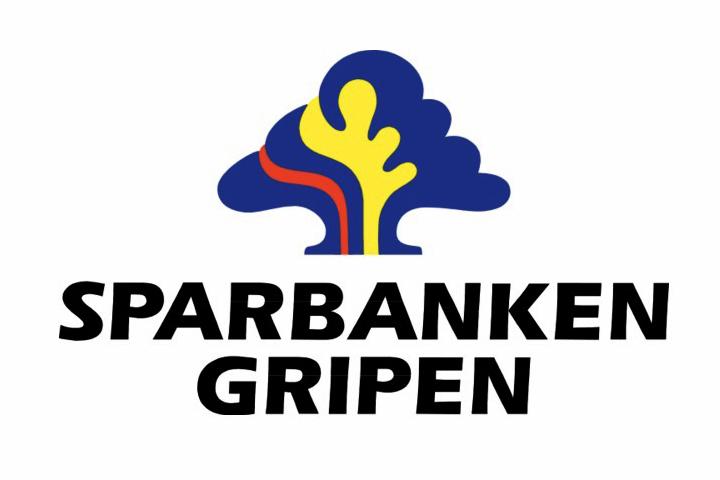
Vårt allra första uppdrag från 1990! Sparbanken hade anlitat en formgivare i New York som hade handritat ett nytt helversalt typsnitt i samband med bankens omarbetade grafiska identitet (med ny stilistisk logotyp och allt). Vi fick detta handritade underlag, scannade in och vektoriserade hela alfabetet och tog fram vårt allra första unika företagstypsnitt.
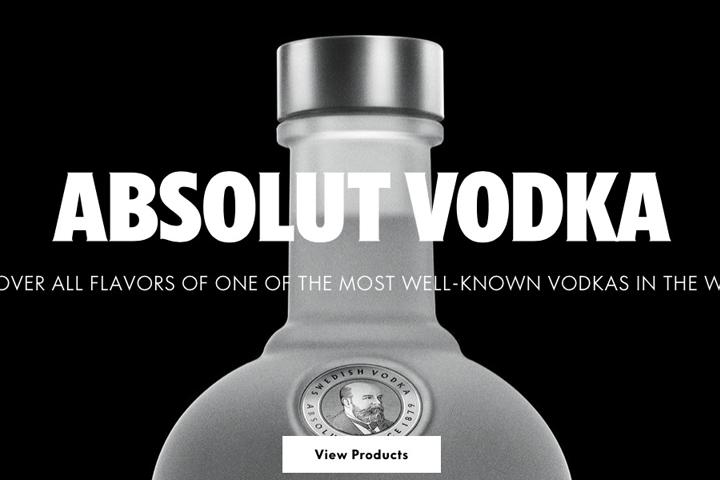
Vi tog fram tre nya vikter med fyra tillhörande kursiver (varav en bakåtlutad), två kondenserade vikter samt en graverad, samtliga för både print och webb (de senare med utökat manuell specialhintning). Förlagan var Absoluts tidigare typsnitt Futura, men med en lite mer samtida touch med influenser från modern humanistisk grotesk.
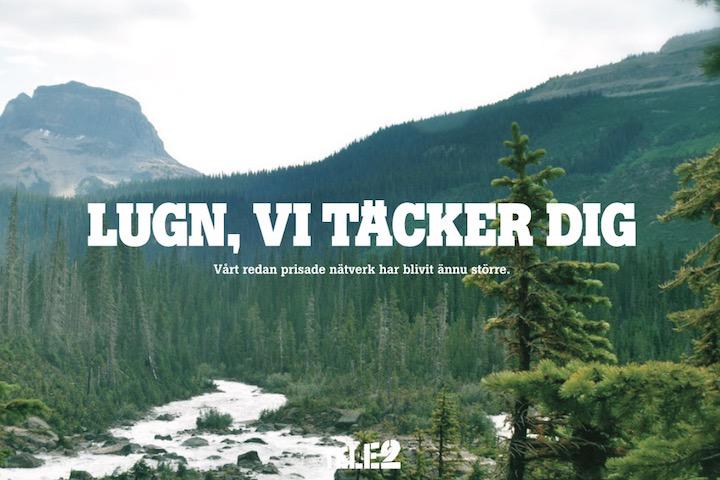
Med Tele2:s befintliga slabseriff-typsnitt som idémässig förlaga fick vi i uppdrag att rita ett helt nytt unikt typsnitt till Tele2, vilket resulterade i de två vikterna Regular och Bold jämte kursiver i såväl rubrik- som löptextanpassat tillriktningsutförande. Vi kompletterade senare samtliga fonter med kyrilliska (ryska) versioner, och ritade även en extrafet helversal Heavy-vikt (enbart avsedd för rubriksättning).
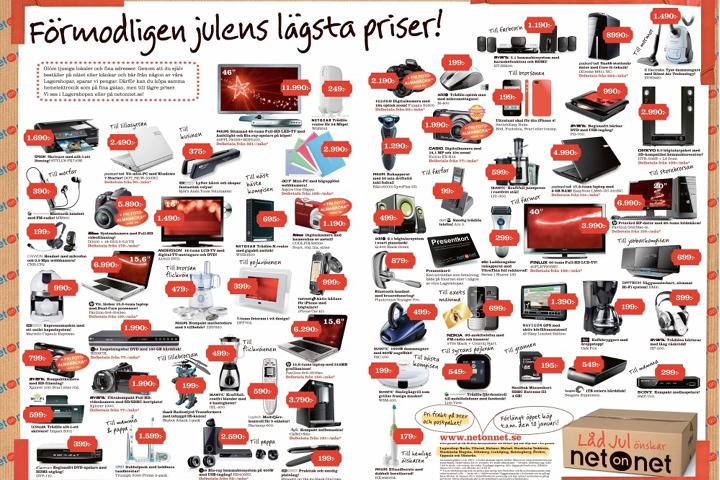
Designbyrån Garbergs behövde ett nytt kampanjtypsnitt till NetOnNet och kom till oss med ett handritat underlag. Vi skannade in, vektoriserade och levererade ett färdigt typsnitt i retur.
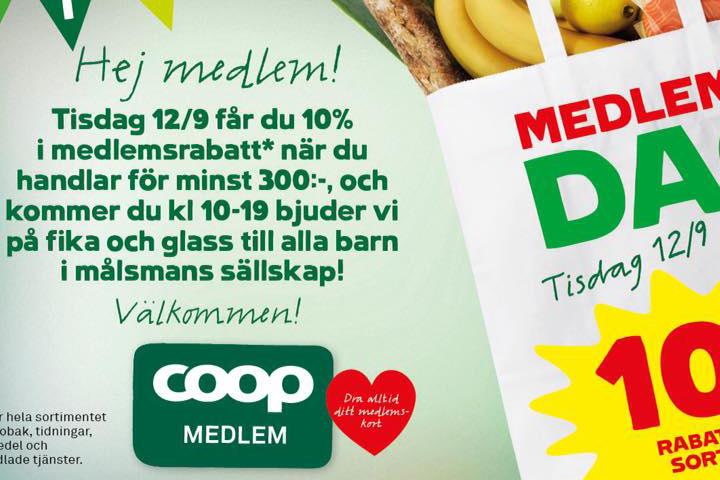
Designbyrån Garbergs levererade handtecknade underlag, vi skannade in, vektoriserade och skapade ett nytt typsnitt med delvisa sammanbindningar och multipla ligaturer. Det nya typsnittet Gröna Konsum Script användes sedan i butiker, på skyltar, på plastpåsar -- ja, överallt. I dag har typsnittet ärvts av Coop som i skrivande stund fortfarande använder det i sin kommunikation.
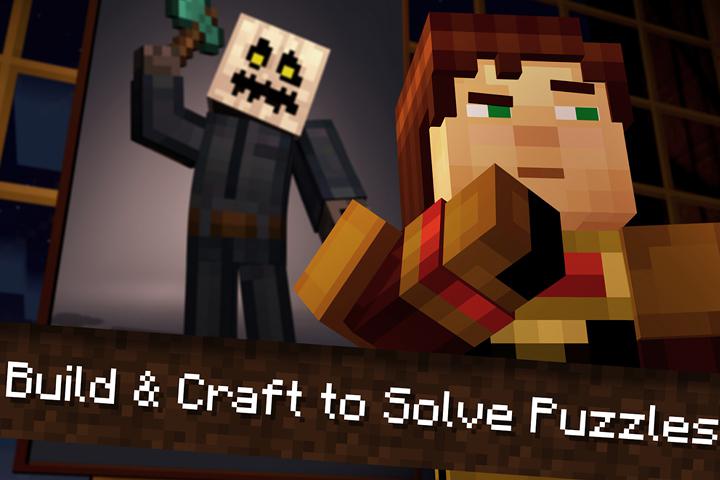
Vi erhöll några få färdiga tecken i bitmappat manér som skissanvisningar direkt från det svenska dataspelsföretaget Mojang (som ligger bakom det internationella succéspelet Minecraft), och fick sedan själva teckna fullständiga alfabet för totalt fyra nya vikter i samma pixellerade utförande (syftet var att återge samma "blockkänsla" som i spelets egna datorgrafik).
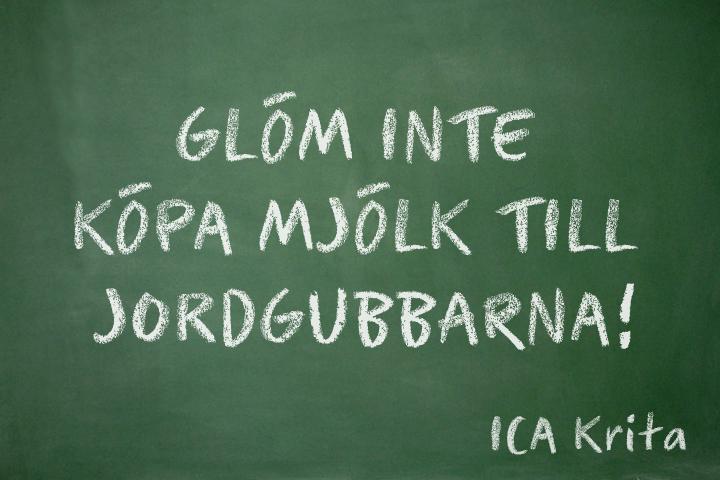
Designbyrån JVD levererade handritat underlag som vi sedan vektoriserade och skapade ett nytt unikt typsnitt utifrån. Underlaget var tecknat med krita och utmaningen bestod i att lyckas återge detta manér på ett så trovärdigt sätt att det framstod för ögat som att budskapet verkligen var skrivet för hand.
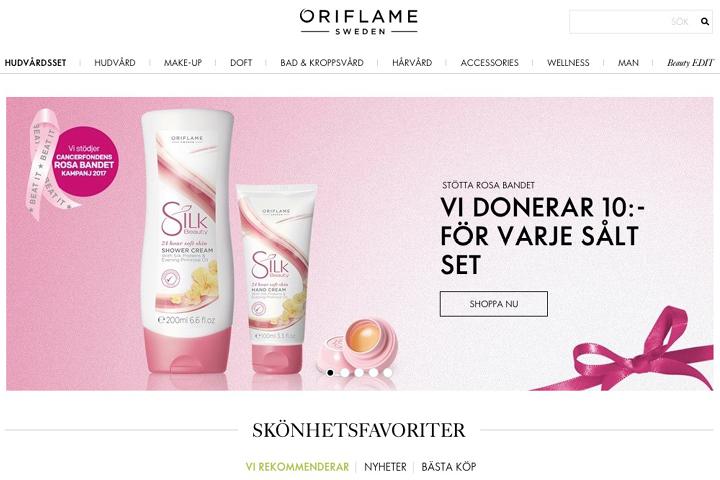
Oriflame hade tidigare använt Futura och kontaktade oss för att ta fram ett helt nytt unikt eget typsnitt med samma grundformspråk som i Futura. Arbetet resulterade i de nya vikterna Regular och Bold jämte tillhörande kursiva snittvarianter, med utökat språkstöd för såväl det grekiska som det kyrilliska (ryska) alfabetet. Vi levererade för både print och för webb, där webbfonterna erhöll en genomarbetad manuell hintning för optimal bildskärmsåtergivning av högsta tekniska kvalitet.
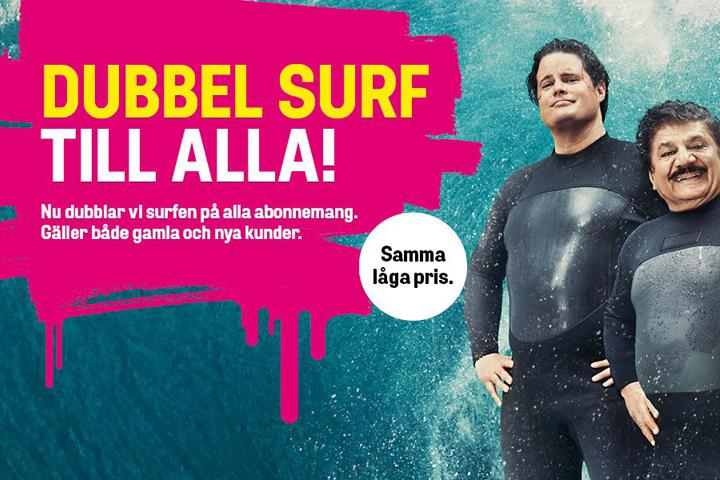
Designbyrån Kurppa Hosk hade hittat ett typsnitt med en del egenheter som man gillade, men ville rita ett helt nytt. Vi fick i uppdrag att hämta inspiration från detta, men rita ett nytt eget unikt typsnitt till Comviq. Ursprungligen tog vi fram två nya vikter med kursiver, efter något år kompletterade vi med ytterligare en mellanvikt med kursiv.
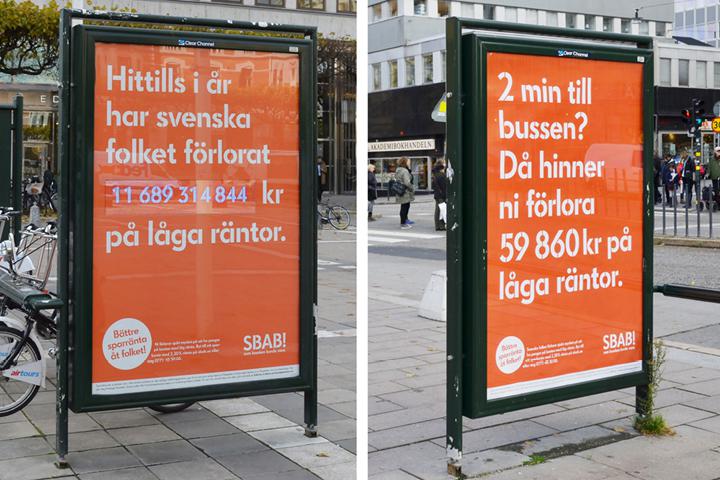
På designbyrån Le Bureau hade man skissat med Futura som nytt typsnitt för SBAB, men ville samtidigt ta fram ett eget unikt typsnitt. Vi fick i uppdrag att med Futura som visuell förlaga teckna vikterna Regular och Bold, jämte kursiver, samt en ny Bold-vikt i stencilerat manér. Dessa fonter levererade vi sedan för både print och webb.
Designbyrån Honesty hade valt ett handritat helversalt typsnitt till Scandic Hotels, men ville komplettera detta med ett gement alfabet. Vi tog kontakt med tillverkaren i Brasilien och fick deras skriftliga godkännande att själva rita och lägga till detta. Vi kompletterade även med utökat språkstöd för det kyrilliska (ryska) alfabetet, både versalt och gement, och tog dessutom fram alternativvarianter av alla tecken för att kunna variera och ge ett mer dynamiskt intryck. Till sist programmerade vi även typsnittet så att denna teckenrotation kunde ske med automatik, så att samma tecken aldrig upprepades invid sig självt.
Transportstyrelsen hade fått klagomål från polisen om att deras olika OCR-system hade problem att avläsa dåvarande registreringsskyltar. Transportstyrelsen kontaktade därför oss och gav oss i uppdrag att rita det typsnitt som i dag används på alla nya registreringsskyltar. Tyvärr förelåg vissa tekniska begränsningar i skyltproduktionen som förhindrade ett typografiskt optimalt typsnitt (man skulle kunna säga att funktionaliteten i detta fall ”körde över” estetiken...), och vi fick göra en del formmässiga eftergifter för att skyltproduktionen skulle fungera – men polisen blev i alla fall nöjda med resultatet.
Barncancerfonden använde skyltar som bara fanns handtextade och behövde nu ett snarlikt typsnitt. Designbyrån Intellecta hittade ett gratistypsnitt som låg väldigt nära som de bad oss modifiera och feta för att ytterligare överensstämma med det handtextade underlaget så att skillnaden blev försumbar.
Designbyrån Collaborate levererade färdigvektorisat handtecknat Illustrator-underlag, vi skapade utifrån detta ett nytt typsnitt och tog även fram en kompletterande fetare vikt.
En förteckning över fler än 120 företag, organisationer och myndigheter som har fått egna unika profiltypsnitt som vi har varit med och tagit fram (ovan visar vi endast ett litet urval av dessa):